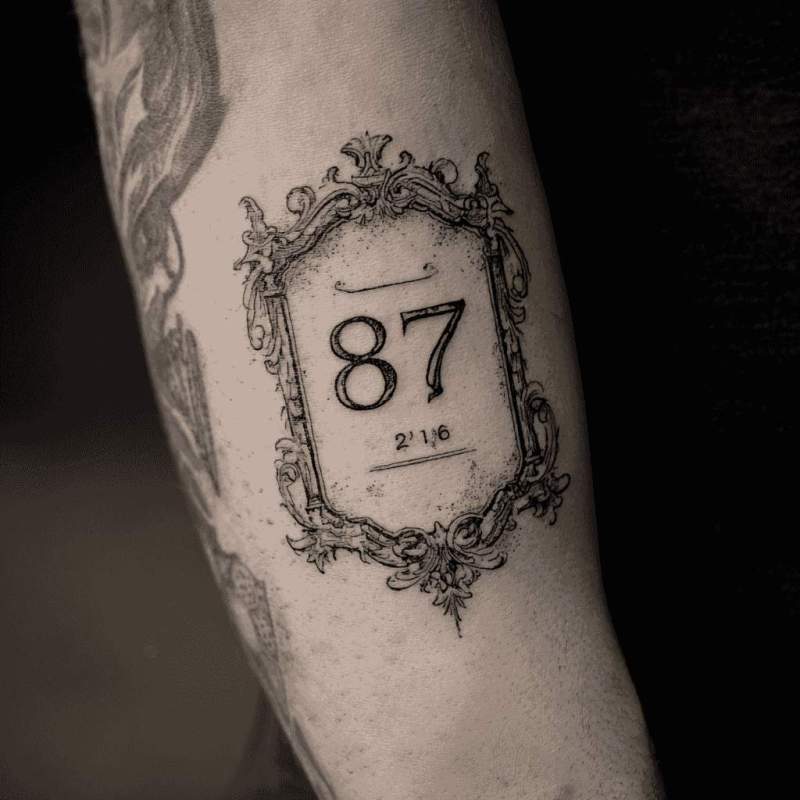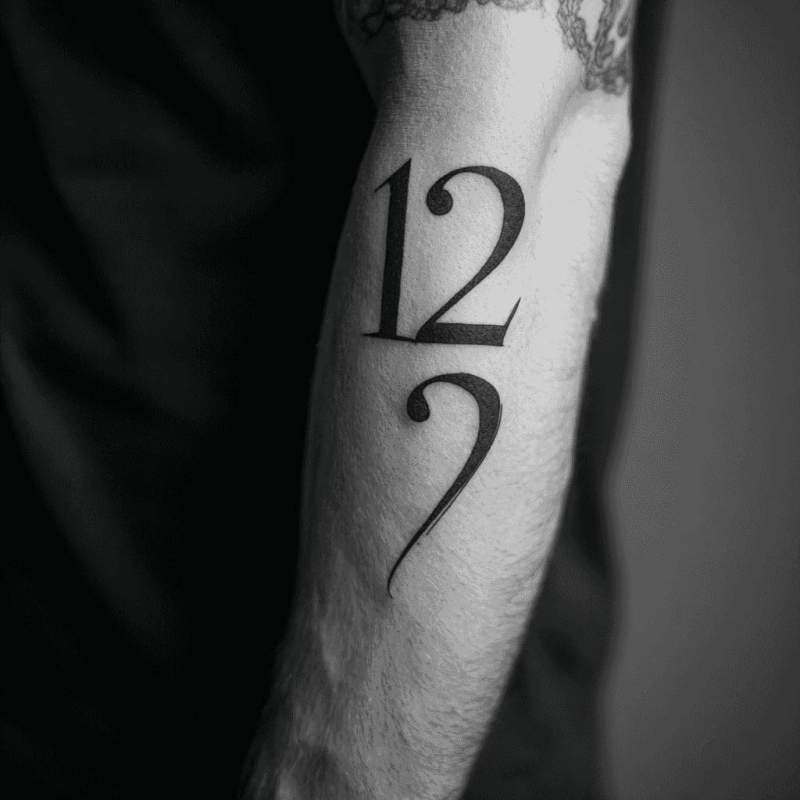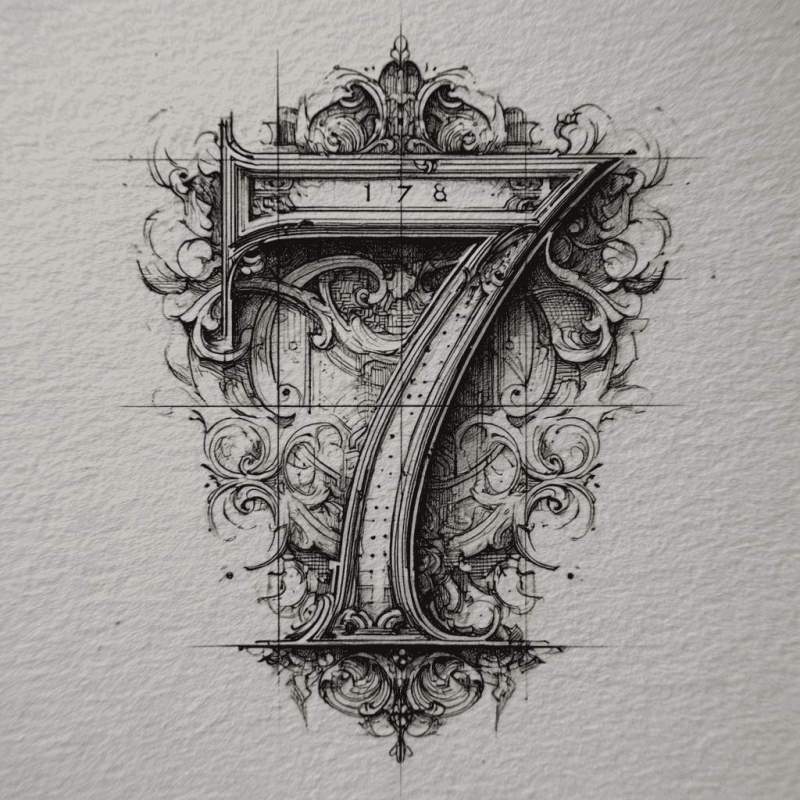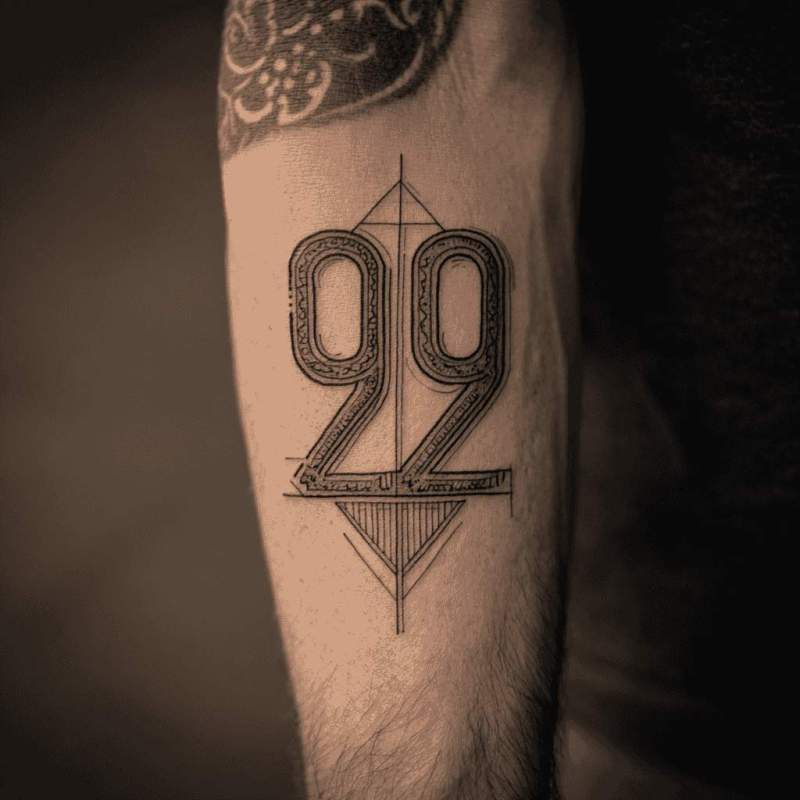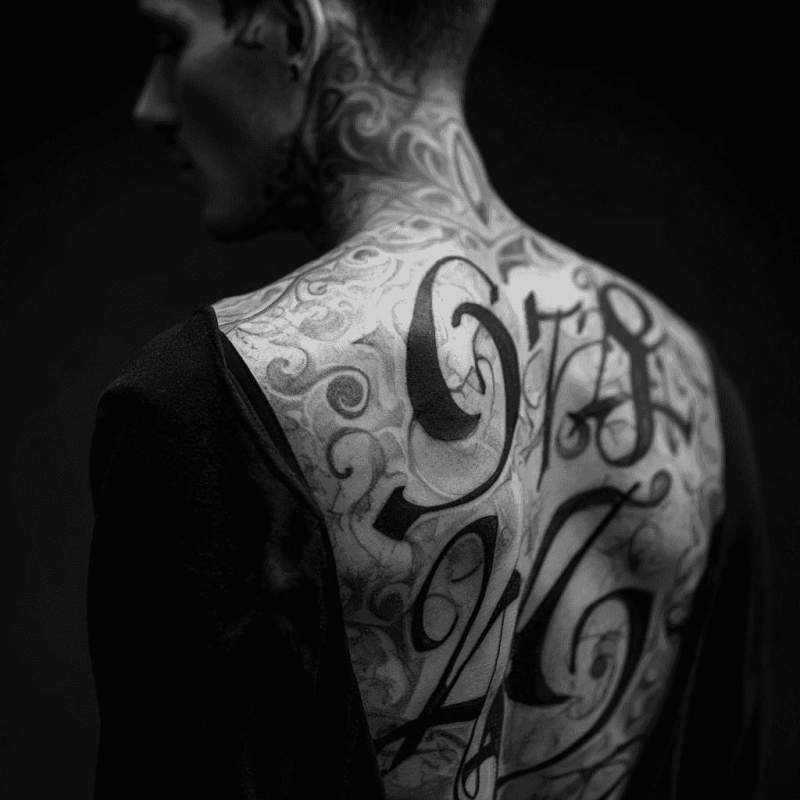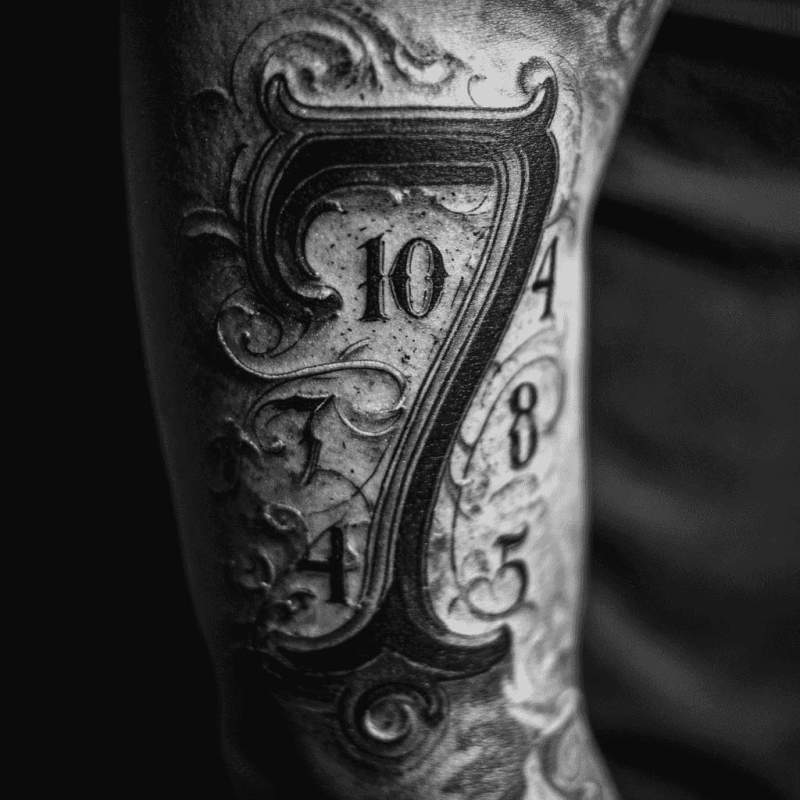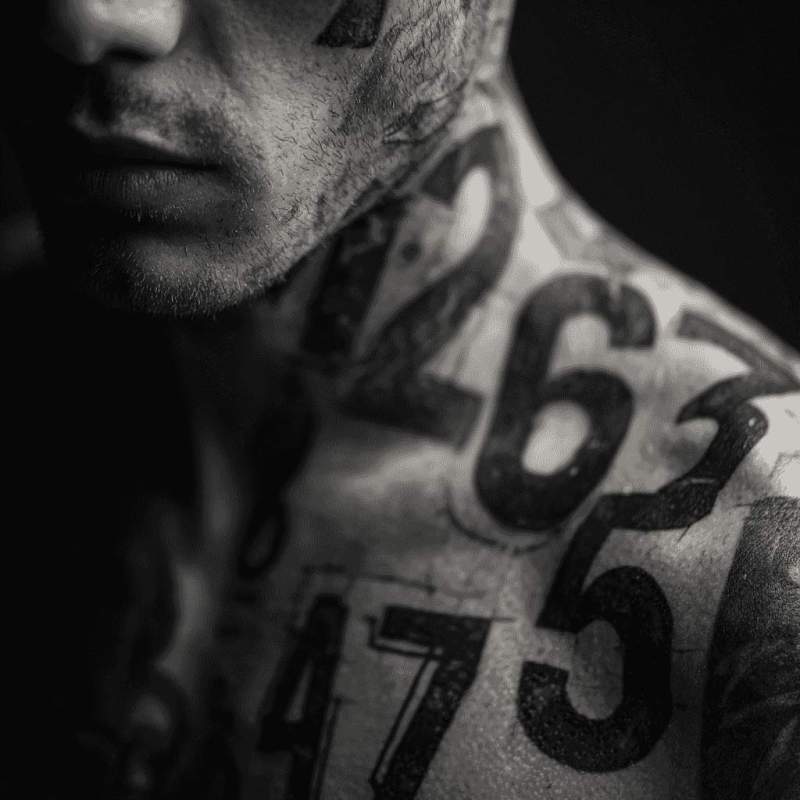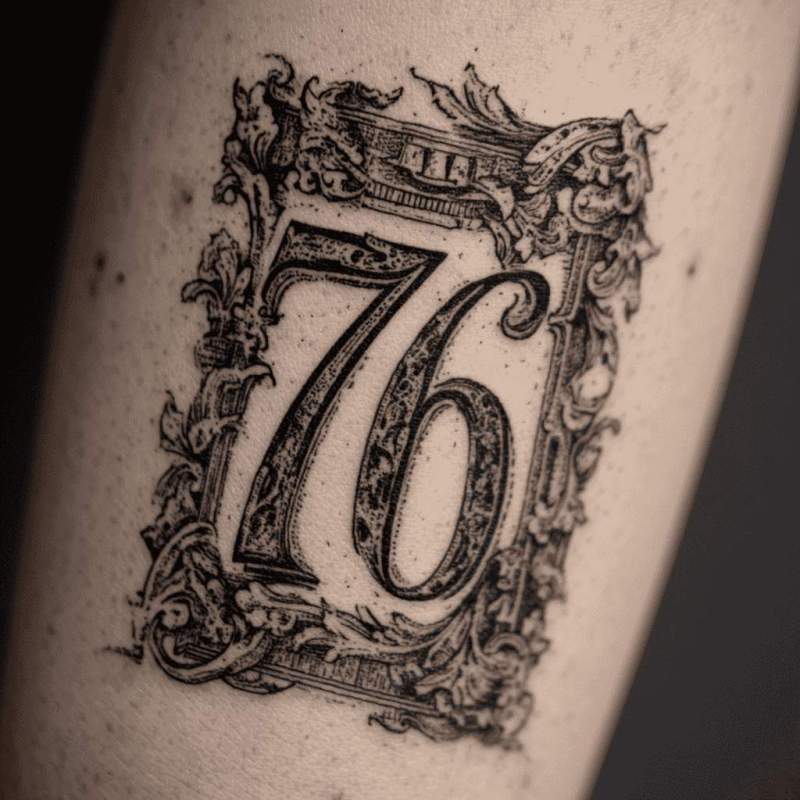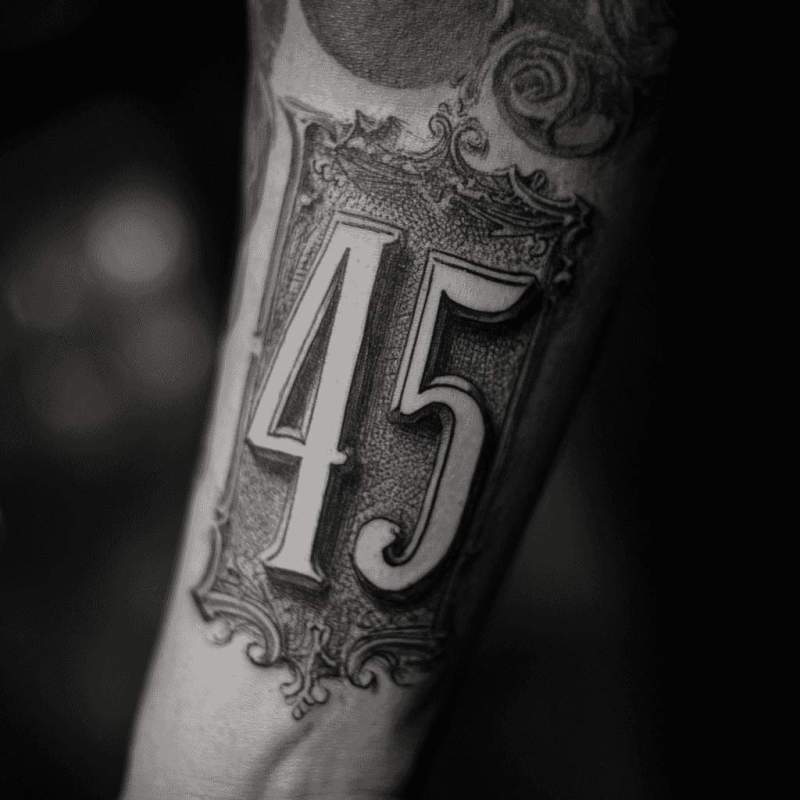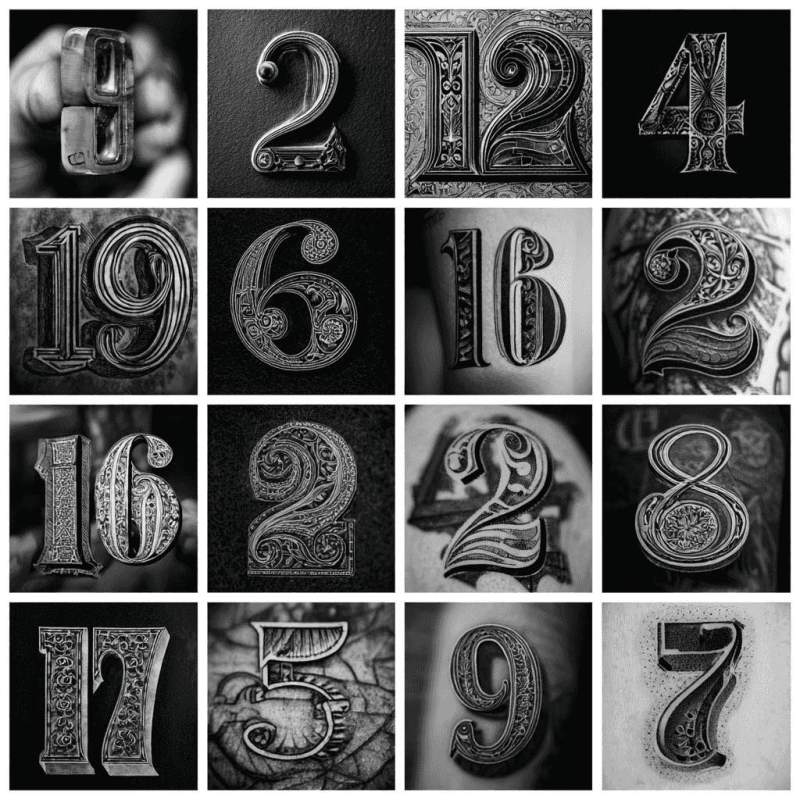
Kalkulierst du mit stylischen Zahlen-Schriftart Tattoos? Die Number-Typography-Tattoo-Meister von Lebende Legend Tattoo in Bern, Schweiz haben die besten numerischen Font-Designs zusammengetragen, um dir mathematische Eleganz-Inspiration zu entfachen.
Welche Bedeutung steckt hinter einem zahlen tattoo schriftart?
Numerische Γ„sthetik wird in Zahlen-Schriftarten-TΓ€towierungen durch verschiedene Typografie-Stile individualisiert. Geburtsdaten, GlΓΌckszahlen oder Koordinaten profitieren von charakteristischen Schrift-Arten. Verschiedene Epochen und Kulturen inspirieren unterschiedliche Zahlen-Darstellungen.